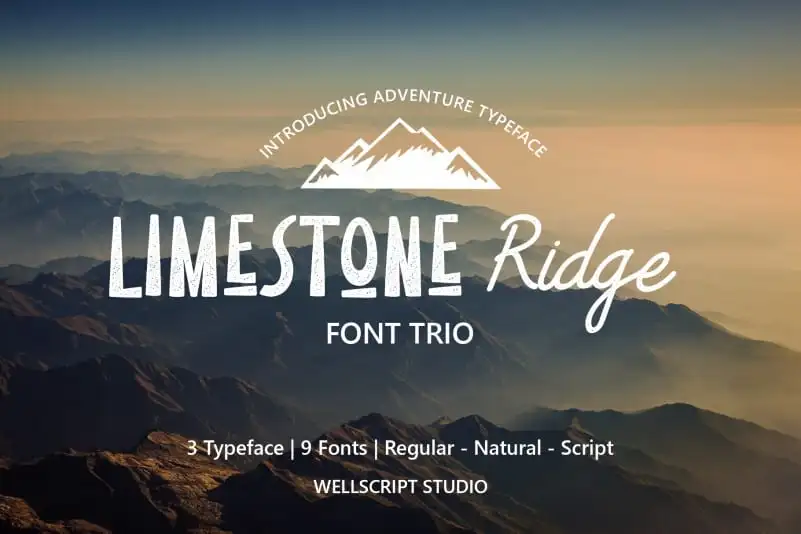
Limestone Ridge – Trio Adventure Font – Download Grátis
A Limestone Ridge – Trio Adventure Font é uma elegante combinação de tipos misturados entre sans-serif e script. Inspirada na atividade aventura, essa tipografia traz um toque único que se assemelha a escrita manual. As linhas do tipo estão suaves, proporcionando um visual encantador com aparência de autêntica escrita à mão. Este conjunto de três estilos (limpo, pressado e selvagem) é uma opção perfeita para designers que buscam uma fonte interessante para textos em ações emocionantes ou atividades outdoor. Ideal para gráficos como nomes de empresas relacionados ao esporte ou o design de materiais promocionais de campanhas de aventura, a Limestone Ridge traz um toque único e inspirador à qualquer projeto que você estiver criando. Sua presença elegante e seu estilo original fazem dela uma escolha ótima para aqueles que desejam dar um salto na criação visual com essa fonte única.